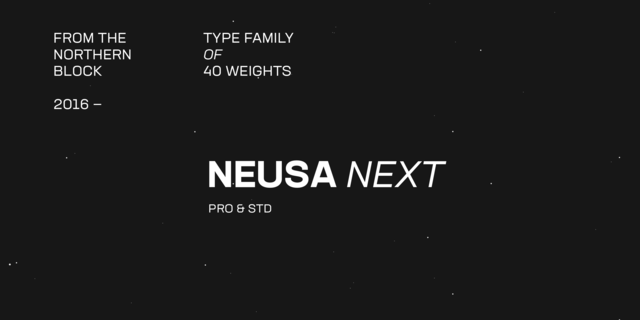
Neusa Next Pro – это семейство геометрических гротесков с широким диапазоном насыщенности и ширины. Гарнитура предоставляет дизайнеру сложную и богатую типографскую палитру. Разработанный и выпущенный как Neusa в 2012 году, проект задумывался как компактное шрифтовое семейство. Подходящий для текста, шрифт был оснащен отличительными характеристиками, которые позволяли ему также работать в акциденции. Сегодня Neusa Next Pro расширяет набор символов до расширенной кириллицы и включает еще три ширины: узкий, обычный и широкий, каждый из наборов начертаний имеет свой индивидуальный характер. Дизайн вдохновлен ранними исследованиями космоса, в том числе культовой обложкой журнала «Life» 1969 года на тему программы Apollo и, конечно, произведениями швейцарского дизайна. Семейство Neusa Next Pro состоит из 20 весов, по пять жирностей на каждую ширину, с соответствующими курсивами, всего 40 начертаний. Возможности OpenType включают локализованные формы для башкирского, болгарского, каталонского, чувашского, голландского, македонского, молдавского, румынского и сербского языков, а также верхние и нижние дроби, пунктуацию с учетом регистра и специальный стилистический набор с иконками космической тематики. Языковая поддержка включает латинские и кириллические алфавиты большинства западноевропейских и центральноевропейских языков, основанных на латинице. Шрифт разработала Мария Пигулевская в 2017 году. Neusa Pro™ является торговой маркой компании The Northern Block.
Ассоциации c начертанием Neusa Next Pro Compact MediumКачества и характер:
точный, ровный, убедительный, прямоугольный, стабильный, твердый, серьезный, надежный, уверенный, сильный, устойчивый, индустриальный, техногенный, статичный, авторитетный, городской, мотивирующий, автоматический, урбанистический, стальной, крепкий, строгий, деловой, современный, монотонный, логичный, прагматичный, практичный, искусственный, холодный, машинный, инженерный, важный, военный, тяжелый, железный, крутой, железнодорожный, чертежный, амбициозный, урбанистичный, архитектурный, Узкий, высокий, гладкий, громкий, космический, футуристичный, умный, рабочий, ответственный
новости, техника, прибор, промышленность, станок, инструмент, электростанция, энергетика, завод, тренажеры, архитектура, наука, ремонт, дизайн, город, урбанистика, инженер, автоматика, институт, космос, ракета, спутник, армия, оружие, машиностроение, порт, конструктор, авиация, самолет, страйкбол, стройка, строительство, небоскреб, технологии, вагон, чертеж, железная дорога, архитектор, Небоскреб, гаджет, девайс, айтишник, айти, IT, футбол, спорт, рабочий, киберспорт, компьютерная игра, селфи Стилистика: